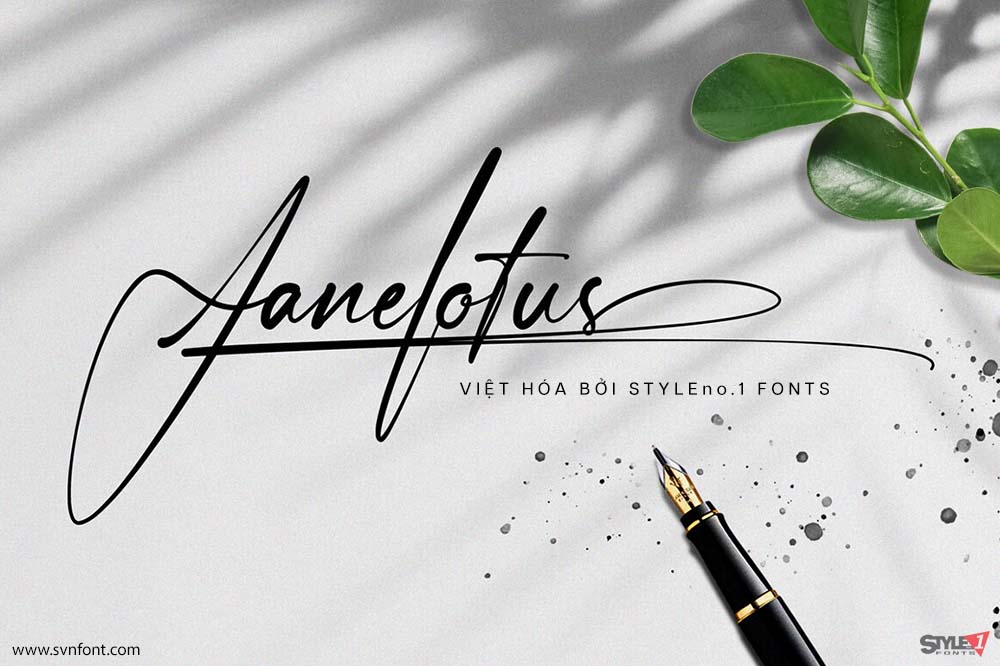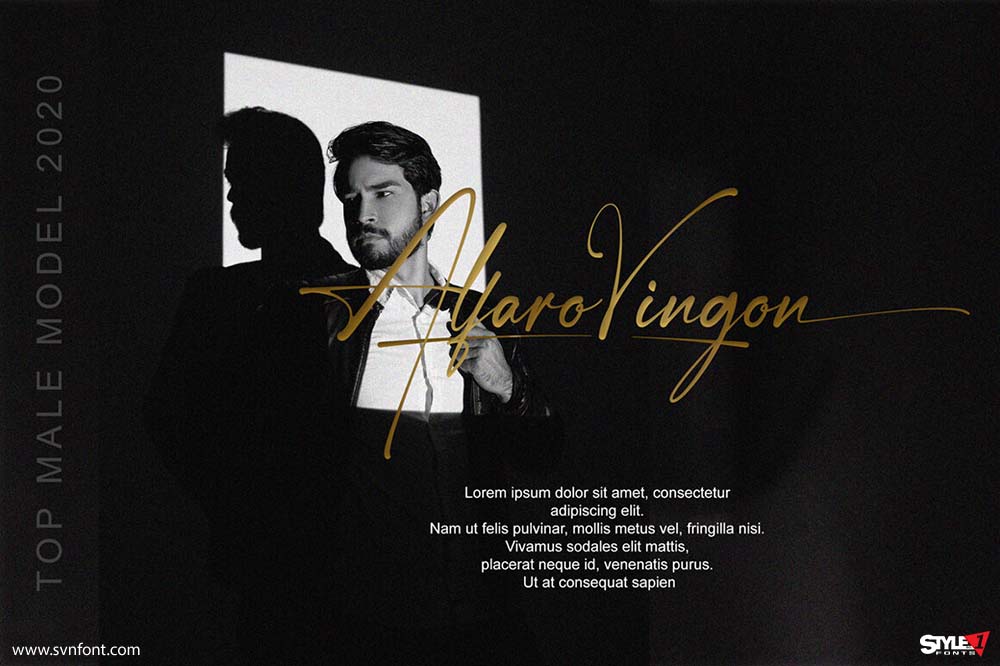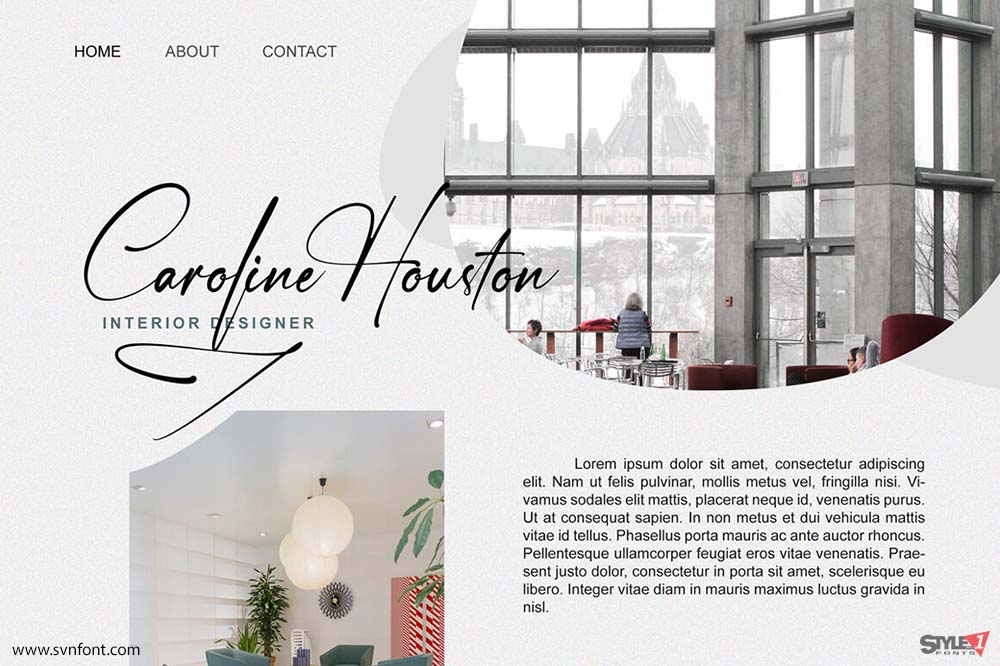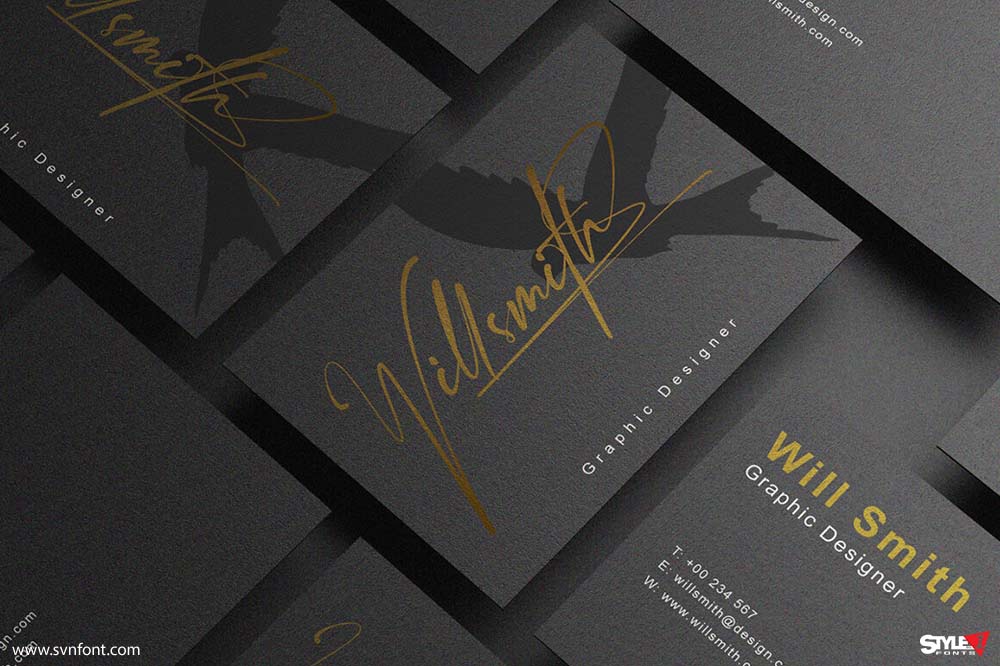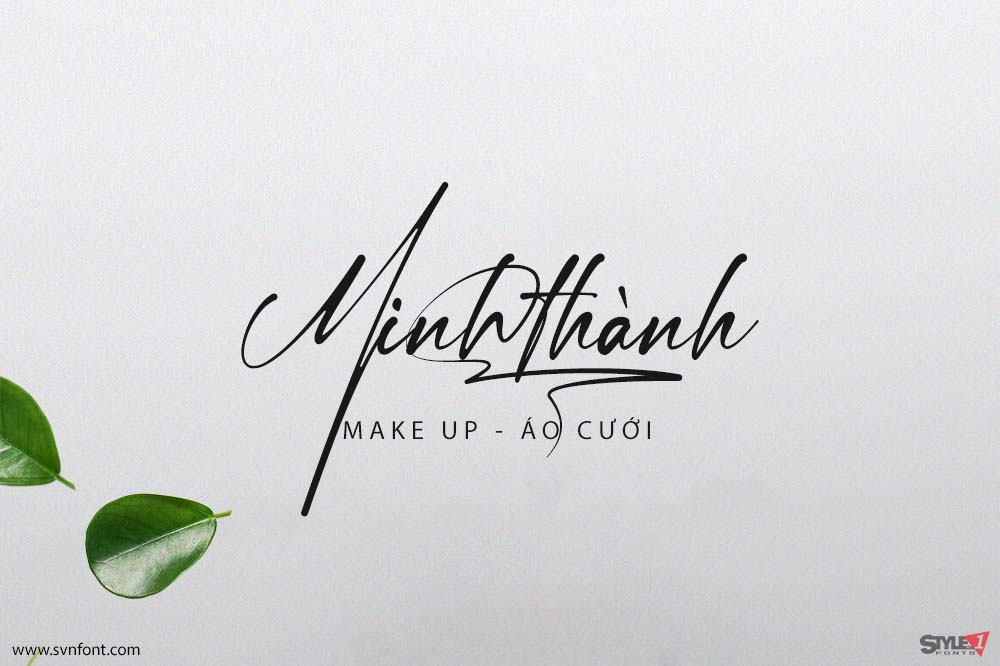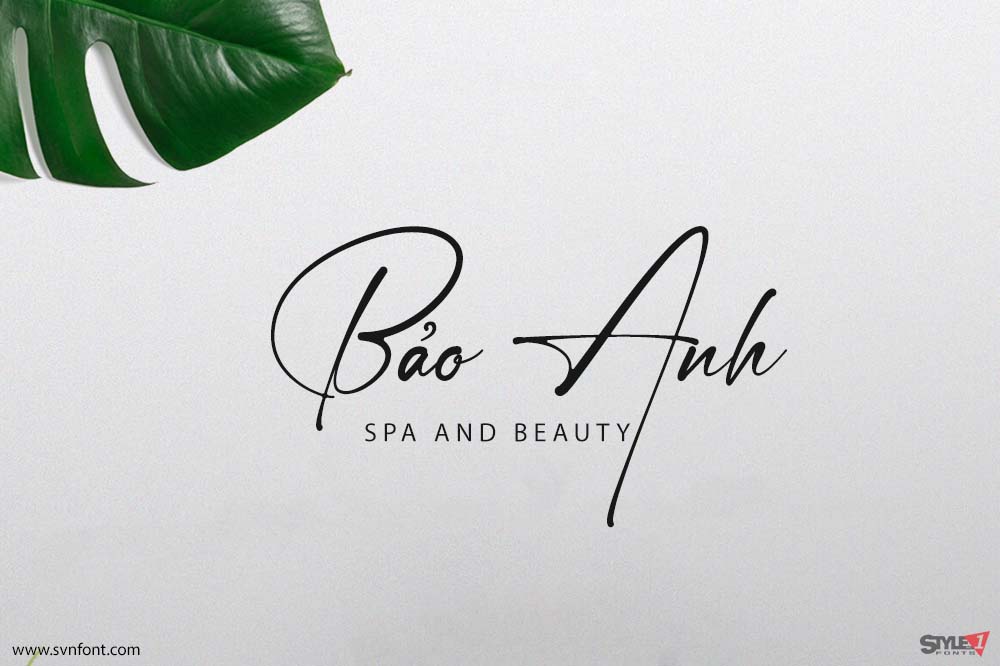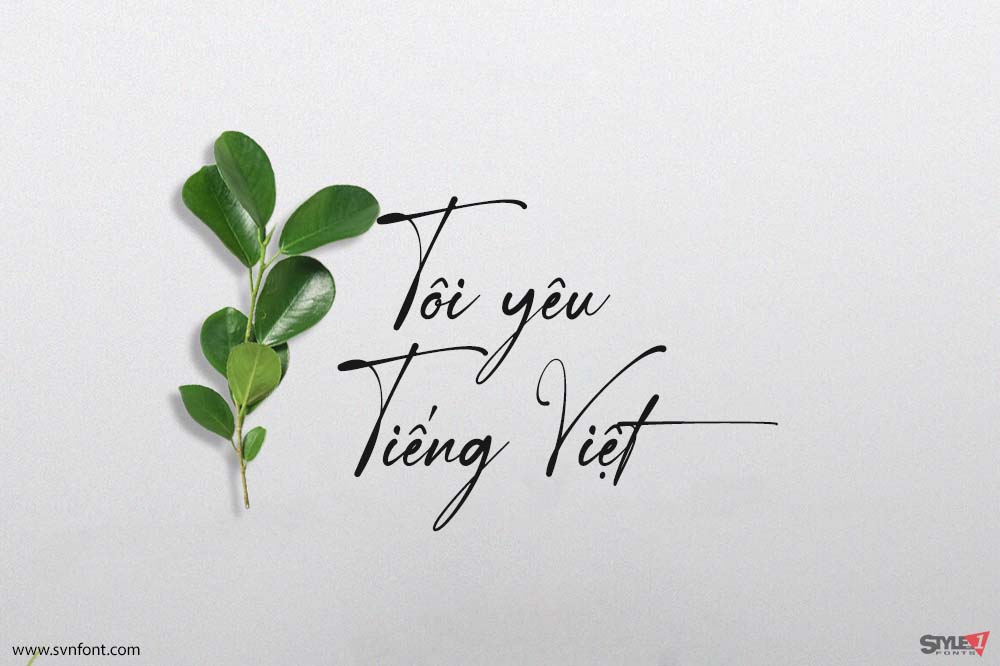
Font Việt Hóa SVN - Janelotus Font Chữ Ký Cho Các Thiết Kế
Janelotus - một signature font hoàn hảo mà những bạn thích font chữ ký nhất định phải có. Nét chữ tự nhiên mô phỏng khá tốt kiểu chữ ký, sẽ là lựa chọn tốt cho các thiết kế: chữ ký, logo - thương hiệu, sản phẩm, nhiếp ảnh...
Nhà thiết kế: Dwi Ahidian
Nhà phát hành: lemonthe
Việt hóa: STYLEno.1 Fonts